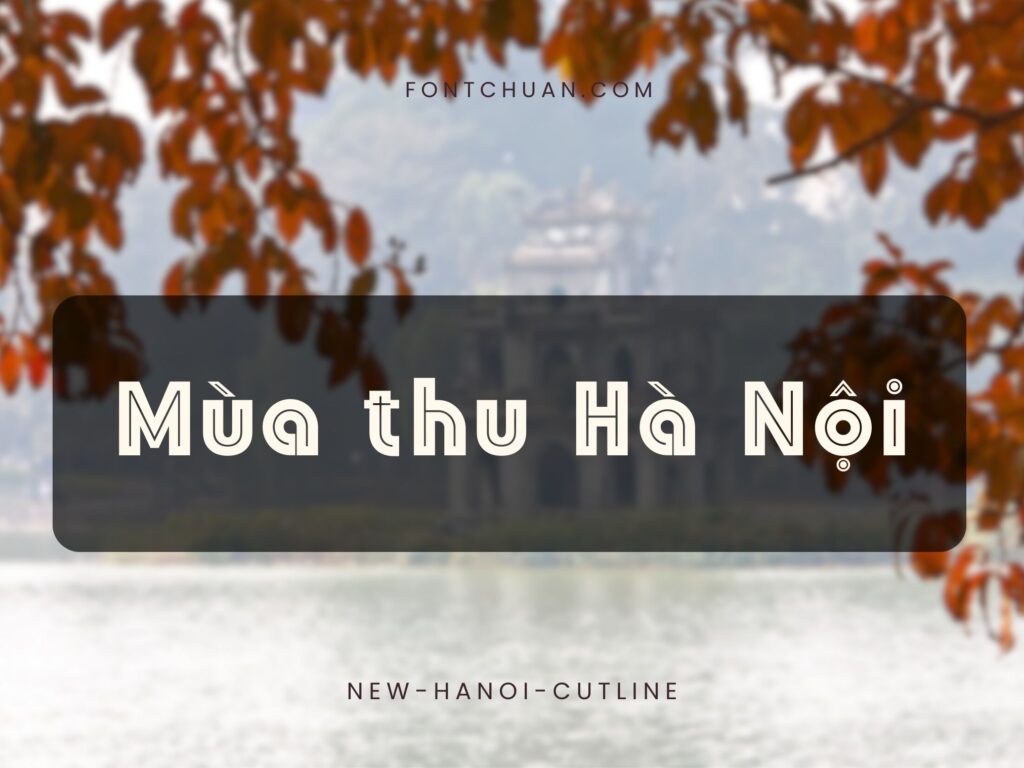
Font New Hanoi Cutline Font Tiếng Việt
New Hanoi Cutline là một font hiển thị cổ điển, được thiết kế dựa trên logo của Báo Hà Nội năm 1957. Font này mang phong cách vintage, tái hiện lại nét đặc trưng của thiết kế đồ họa Việt Nam trong những năm giữa thế kỷ 20. New Hanoi Cutline hỗ trợ tiếng Việt và nhiều ngôn ngữ khác, được sưu tầm và đăng bởi thành viên của Font Chuẩn.
Font có thiết kế độc đáo với các nét chữ đậm, đường cắt sắc nét và cấu trúc chắc chắn, tạo nên sự nổi bật và thu hút. New Hanoi Cutline phù hợp cho các thiết kế mang phong cách retro, như bìa sách, poster, bao bì sản phẩm và nhận diện thương hiệu. Ngoài ra, font này còn có thể kết hợp với font valentine để tạo các sản phẩm lãng mạn, tinh tế như thiệp Valentine, banner hoặc poster dịp lễ tình nhân, mang đến cảm giác vừa cổ điển, vừa ấm áp, gần gũi. Các ngành nghề như quảng cáo, thiệp cưới, giáo dục và bất động sản có thể tận dụng hiệu quả font này. Ngoài ra, New Hanoi Cutline cũng thích hợp cho các sự kiện như Tết, lễ hội, ngày Nhà giáo và Trung thu.